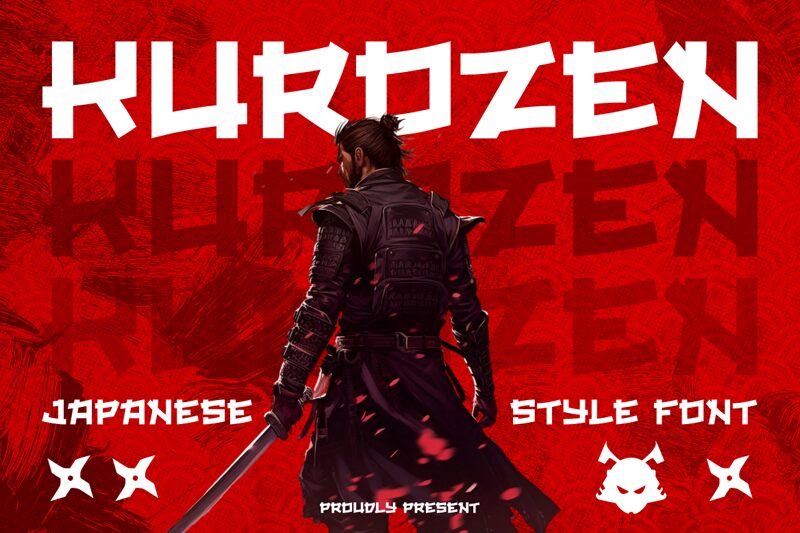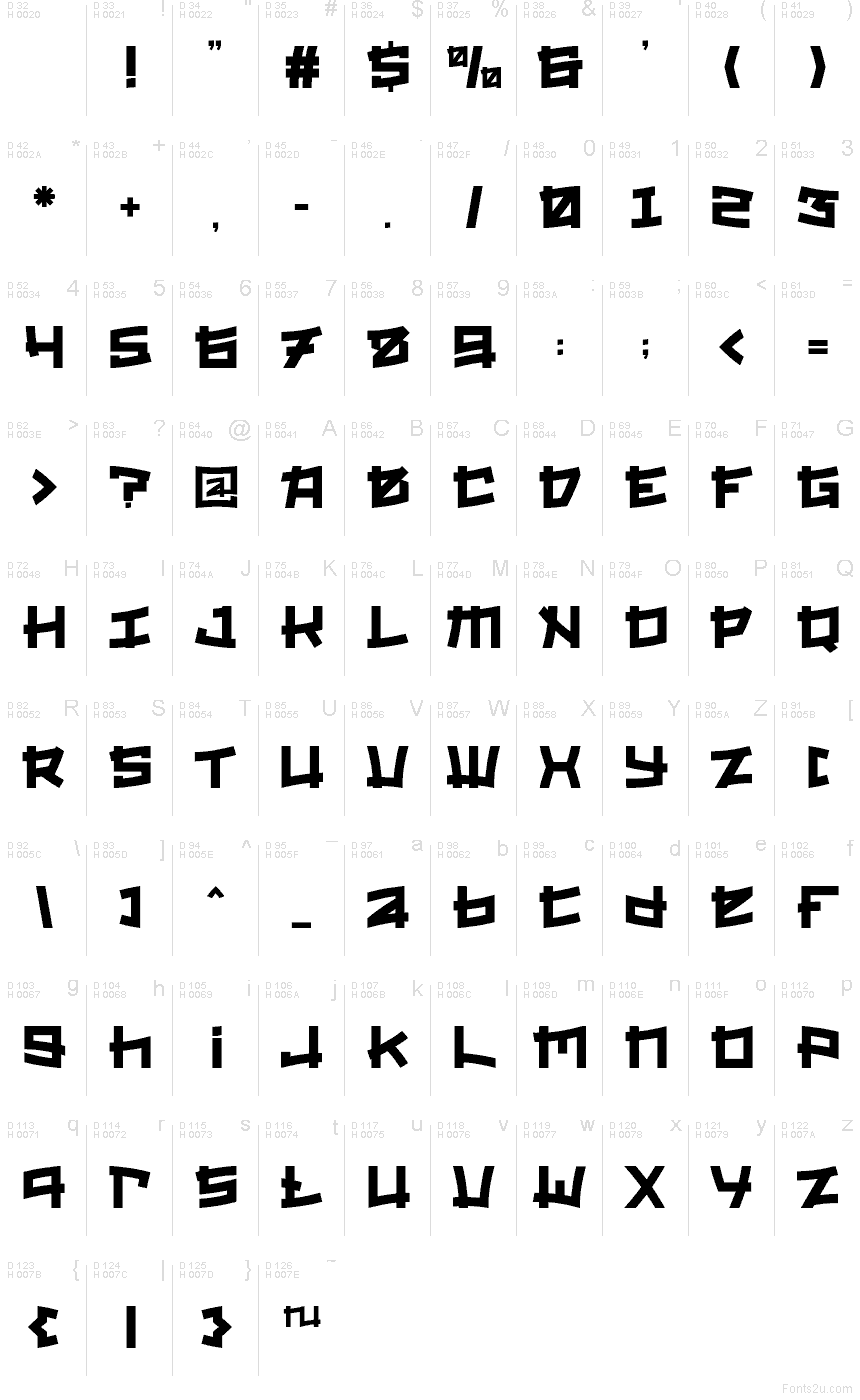
Kurozen od Shanaf Studio je bezplatné, japonsky laděné bezpatkové písmo s rytmem ostrým jako z papíru. Písmena působí blokově a městsky, jsou postavena na těžkých tazích, prudkých úhlech a sekaných rozích, které odkazují na nápisy nebo titulky v manze, aniž by však působila příliš překombinovaně.
Hodí se na plakáty, streetwearovou grafiku, hudební obaly, názvy her, obaly produktů nebo krátké názvy značek, kde potřebujete bezplatný font s výrazným kulturním nádechem namísto neutrálního vzhledu. Použijte jej na titulky nebo kompaktní loga – těsné, zubaté siluety dodávají i krátkým slovům napjatý, grafický říz, který nejlépe vynikne, když mají písmena prostor dát o sobě vědět.